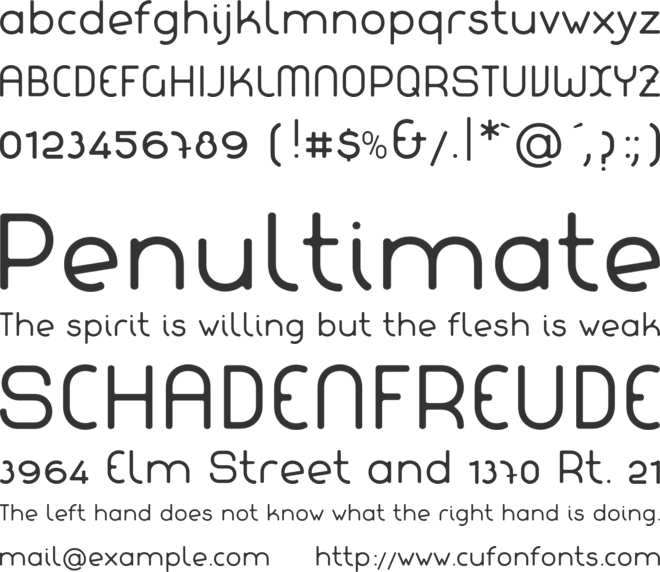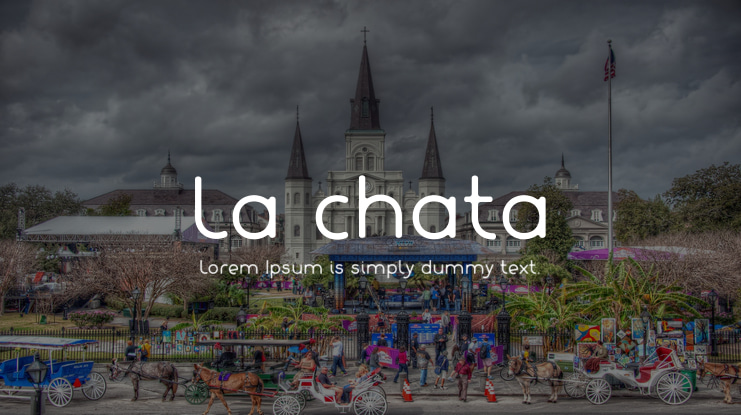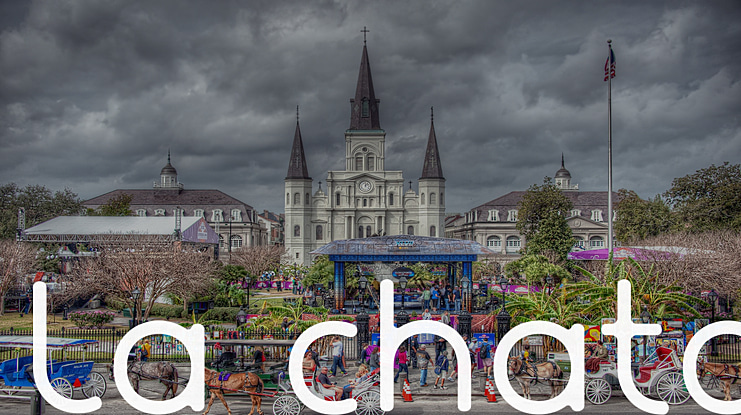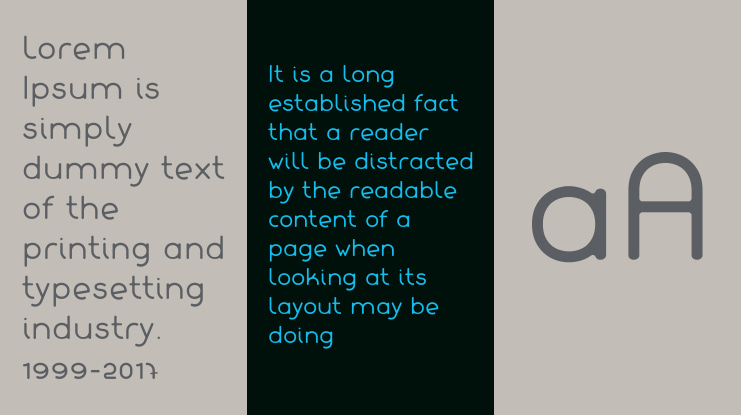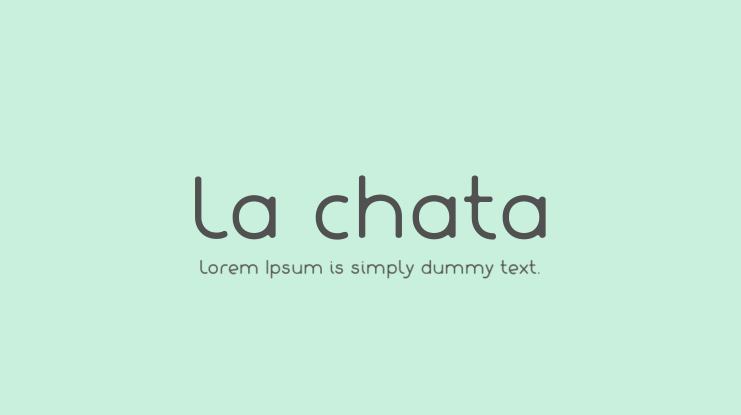
La chata Font
Fernando Haro
Esta es una tipografía de palo seco uniforme, con acabado redondeado en las terminaciones de las astas, ápices, vértices, colas o espolones, también en las uniones con el asta de los travesaños, barras y hombros.